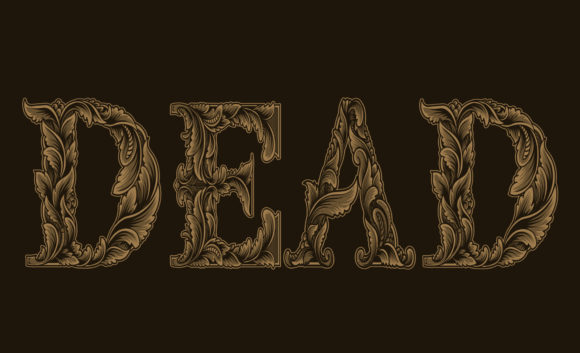
Vintage Death Calligraphy Fonts
適切なデザイン要素を見つけるのは難しい場合がありますが、Vintage Death Calligraphy Fontsは作品を即座に引き立てる優れたコレクションを提供します。
POD(オンデマンド印刷)製品、結婚式の招待状、またはソーシャルメディアのグラフィックを作成している場合でも、Vintage Death Calligraphy Fontsは理想的です。